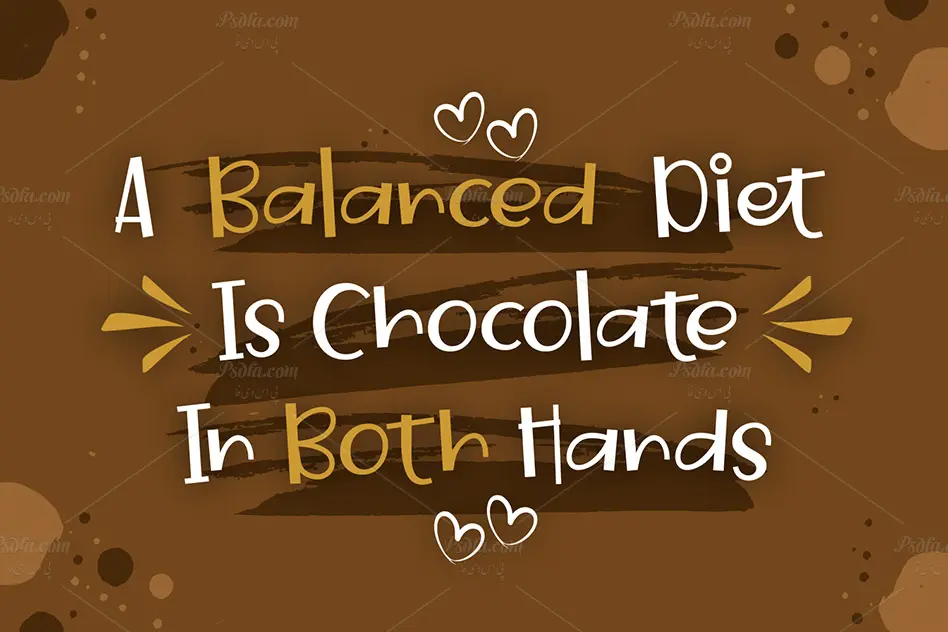
فونت فانتزی کودکانه و فوق العاده زیبای Sweet Choco
فونت فانتزی کودکانه
در این مطلب شاهد فونت فانتزی کودکانه و فوق العاده زیبای Sweet Choco مناسب جهت استفاده در طراحی و گرافیک می باشید. این فونت زیبا در قالب یک فایل otf بر روی سایت قرار گرفته است که با نصب آن در پوشه فونت های سیستم ، قادر به استفاده از این فونت در تمام نرم افزارهای گرافیکی و ویرایشگر متن از جمله نرم افزار فتوشاپ ، افترافکت ، مجموعه نرم افزار آفیس و … خواهید بود. فونت Sweet Choco در وزن معمولی (Regular) طراحی شده است که از آن می توان در طراحی انواع کارت تبریک ، کارت پستال ، قاب عکس ، پوستر ، بنر ، طراحی بر روی تی شرت ، چاپ بر روی ماگ و … استفاده نمود.